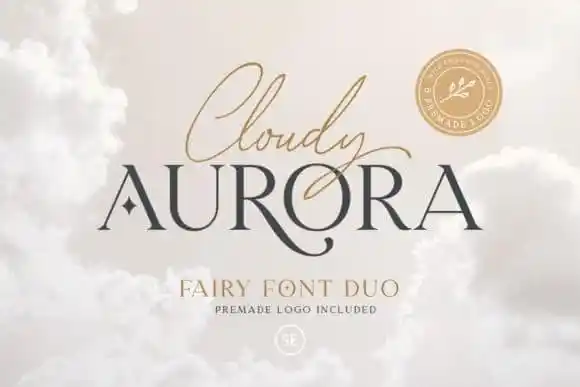
Cloudy Aurora Handwritten Font – Download Grátis
A Cloudy Aurora Handwritten Font é uma escolha perfeita para aqueles que procuram um estilo elegante e único no seu design. Essa font script monoline tem um toque natural e sofisticado, criada pela saridezra e disponibilizada no site da 99designs. Este tipo de letra é tão versátil quanto incrível, adequando-se a uma variedade impressionante de projetos, elevando-os para altos níveis de criatividade e originalidade. Adicionar esta fonte aos seus próprios ideias de design cria um efeito que captura a atenção do espectador, tornando suas criações mais vibrantes e fascinantes. Independentemente do tipo de projeto em que estiver aplicada – seja em logotipos, anúncios ou até mesmo artes gráficas – a Cloudy Aurora Handwritten Font adicionará um toque único que destacará sua marca. Engane-se ao pensar nisso!